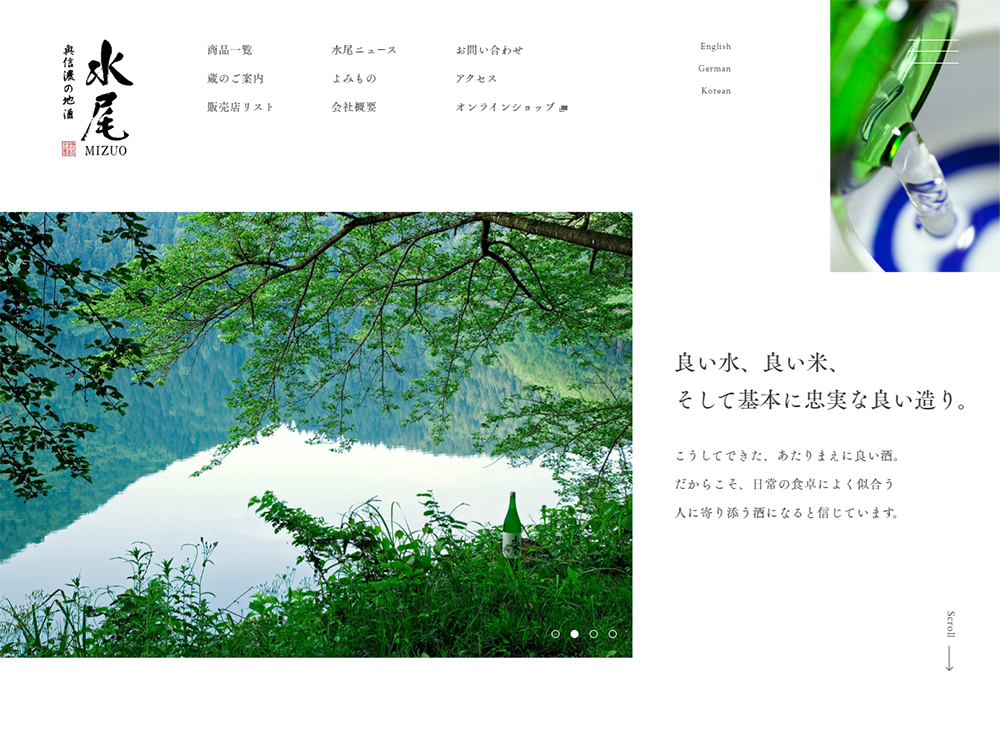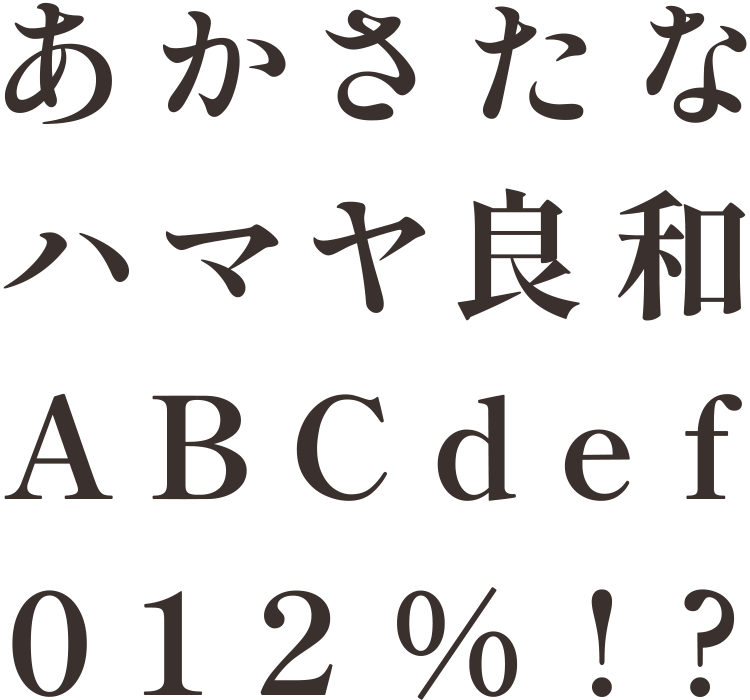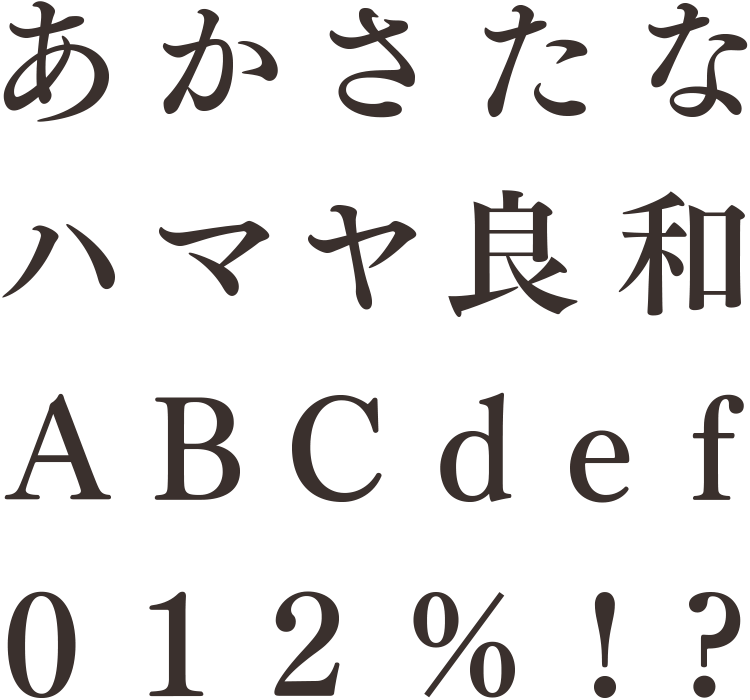
筑紫Aオールド明朝 B
- 全6ウエイト
力強い打ち込みや伸びやかなはね・はらいが特徴的な、オールドスタイルの明朝体フォント。ふところの締まったデザインが「文字らしさ」を際立たせ、組んだ時に“音”を発するような味わい深い表情を生み出します。「筑紫オールド明朝」の一部がリデザイン・6ウエイト展開されたもので、見出しから本文まで対応可能に!
デザイナー
藤田重信様